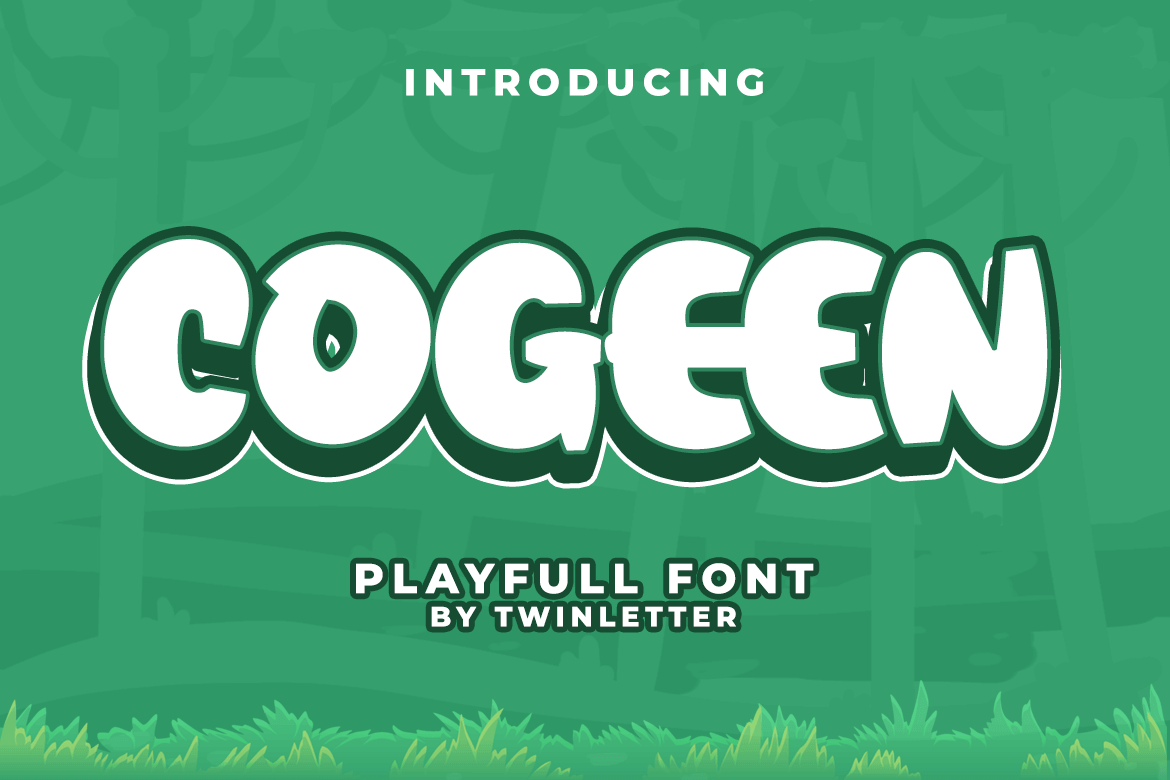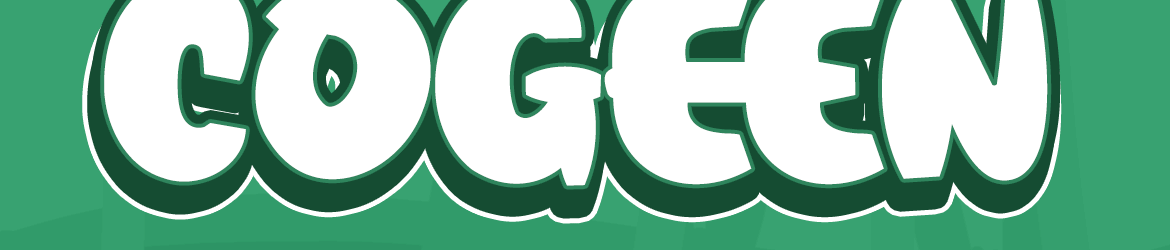
Esta fonte é perfeitamente adequada para trabalhos que requerem destaque visual, seja no design de materiais impressos ou na criação de vídeos e outros tipos de conteúdo online. Introduzida pelo designer twinletter, esta é uma tipografia display projetada para criar um impacto notável em qualquer projeto a qual ela se encaixa. Ela foi concebida com o objetivo de destacar-se, garantindo que seus trabalhos sejam memoráveis e capazes de deixar uma impressão poderosa e sedutora. Seja você criando cartazes ou logos, desenvolvendo materiais para redes sociais ou produzindo conteúdo multimídia, esta fonte estará sempre pronta para intensificar a presença visual do seu projeto.